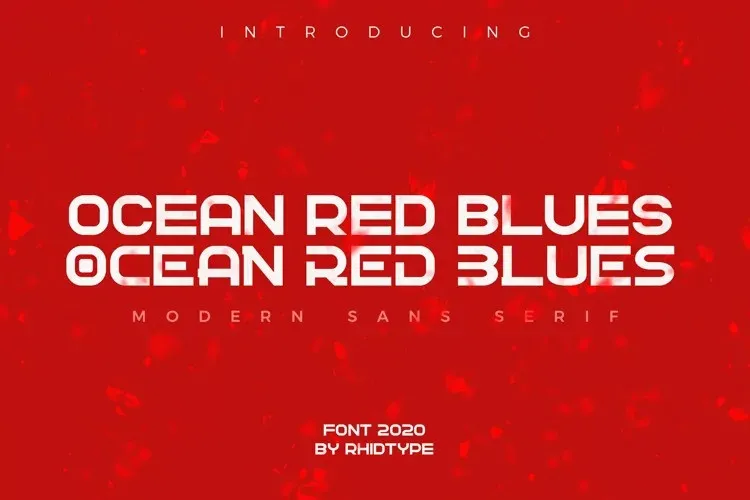
Ocean Red Blues Font – Download Grátis
Esta é uma fonte sans serif moderna criada pelo designer RHID TYPE. Suavemente elegante e idealmente adequada para ambientes futuristas e inovadores, ela se destaca perfeitamente como uma fonte de display para grandes títulos e subtítulos menores. Combine esta fonte com imagens para realmente agradar e encantar seus destinatários. E seu propósito é claro: tornar um espaço mais moderno e inspirador. Com os tons suaves e levemente futuristas desta fonte, ela se adequa perfeitamente para ambientes de tecnologia avançada ou produtos inovadores. Compostas com imagens, esta fonte poderá reforçar ainda mais o seu design, resultando em um impacto visual forte que encanta e impressiona os usuários. Engane-se se acha que isso não é algo especial; aqui está uma fonte de qualidade que pode dar aquele toque único ao seu projeto.